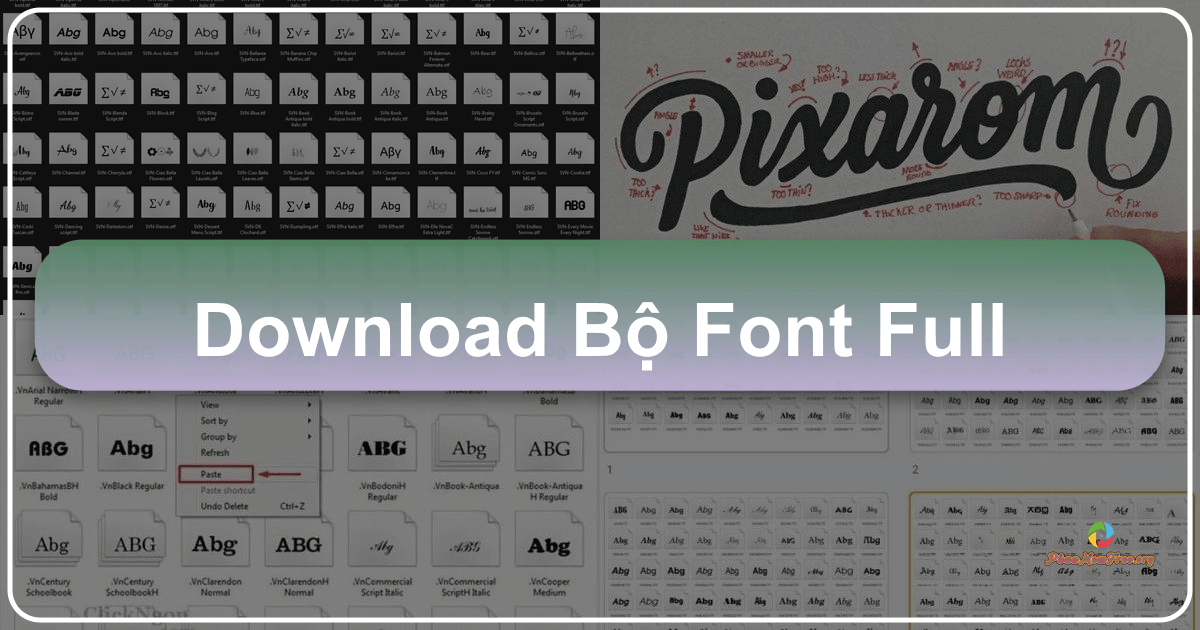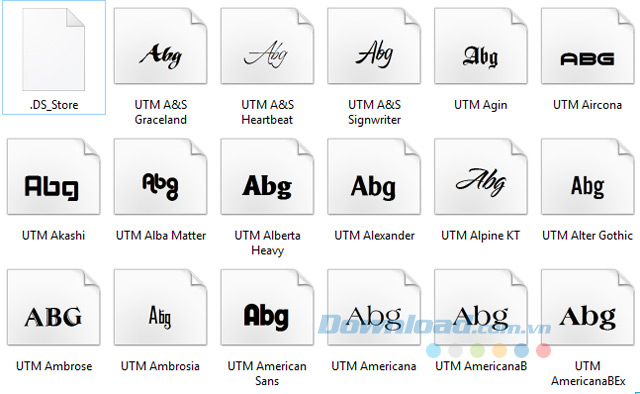
Bài viết này giới thiệu chi tiết về “Bộ Font Full”, một bộ sưu tập font chữ tiếng Việt phong phú và đa dạng, đáp ứng hầu hết nhu cầu sử dụng của người dùng. Bộ font này được cung cấp miễn phí, với dung lượng nhỏ gọn (5,2 MB) nhưng chứa đựng một kho tàng font chữ, giúp người dùng dễ dàng lựa chọn và sử dụng cho nhiều mục đích khác nhau. Tương thích với hầu hết các hệ điều hành Windows từ XP đến 11, Bộ Font Full là một công cụ hữu ích cho cả người dùng phổ thông lẫn các nhà thiết kế chuyên nghiệp.
Tổng quan về Bộ Font Full:
Bộ Font Full là một tập hợp khổng lồ các font chữ tiếng Việt phổ biến nhất hiện nay. Nó không chỉ bao gồm các font chữ cơ bản thường dùng trong soạn thảo văn bản, mà còn tích hợp nhiều font chữ nghệ thuật, font thư pháp, đáp ứng nhu cầu sáng tạo của các nhà thiết kế đồ họa, người làm thiết kế, hay đơn giản là những ai yêu thích sự đa dạng và độc đáo trong văn bản của mình.
Việc sở hữu Bộ Font Full giúp giải quyết triệt để vấn đề thiếu font chữ trên máy tính, một lỗi khá phổ biến gây ra nhiều khó khăn trong quá trình sử dụng máy tính. Thay vì phải tìm kiếm và tải từng font chữ riêng lẻ, gây mất thời gian và công sức, người dùng chỉ cần tải và cài đặt một lần duy nhất là có thể truy cập vào hàng trăm font chữ khác nhau, sẵn sàng phục vụ mọi nhu cầu.
Nội dung của Bộ Font Full:
Bộ Font Full bao gồm đầy đủ các loại font chữ thuộc nhiều bảng mã khác nhau, nổi bật là:
- Font Unicode: Đây là loại font chữ phổ biến nhất hiện nay, hỗ trợ hầu hết các ký tự tiếng Việt có dấu và các ngôn ngữ khác trên thế giới. Việc sử dụng font Unicode đảm bảo tính tương thích cao giữa các phần mềm và hệ điều hành khác nhau.
Font TCVN3: Đây là loại font chữ chuẩn của Việt Nam, được sử dụng rộng rãi trong các văn bản chính thức, tài liệu hành chính.
Font VNI: Một loại font chữ tiếng Việt phổ biến khác, được nhiều người sử dụng nhờ khả năng hiển thị tốt và độ tương thích cao.
Font UTM: Loại font chữ này cũng được tích hợp trong bộ Font Full, mang đến sự đa dạng về kiểu dáng và phong cách chữ viết. Đặc biệt, Bộ Font UTM nổi bật với nhiều kiểu chữ khác nhau, từ những kiểu chữ đơn giản đến những kiểu chữ nghệ thuật phức tạp.
Ngoài ra, Bộ Font Full còn chứa nhiều font chữ khác nhau về kiểu dáng, đáp ứng nhiều sở thích và mục đích sử dụng. Ví dụ, nếu bạn cần viết thư pháp, những kiểu chữ bay bổng, mềm mại, thì các font chữ thư pháp trong bộ Font Full sẽ là lựa chọn lý tưởng. Nếu bạn cần những font chữ đơn giản, dễ đọc cho văn bản thông thường, thì những font chữ như Time New Roman, Arial,… cũng có mặt đầy đủ.
Tính năng chính của Bộ Font Full:
- Hỗ trợ đa dạng font chữ tiếng Việt và tiếng Anh: Bộ Font Full không chỉ giới hạn ở các font chữ cơ bản mà còn bao gồm nhiều kiểu font chữ khác nhau, từ font chữ thông thường như Unicode, VNI, VnTime đến các font chữ nghệ thuật như font thư pháp, font nét bút, font ông đồ,… Sự đa dạng này giúp người dùng có nhiều lựa chọn phù hợp với từng mục đích sử dụng.
Kết luận:
Bộ Font Full là một bộ sưu tập font chữ tiếng Việt hoàn chỉnh và tiện dụng. Với sự đa dạng về kiểu dáng, độ tương thích cao và cách cài đặt đơn giản, Bộ Font Full là một công cụ hữu ích cho mọi người dùng, từ người dùng thông thường đến các nhà thiết kế chuyên nghiệp. Việc tải về và sử dụng Bộ Font Full sẽ giúp người dùng tiết kiệm thời gian, công sức và mang đến trải nghiệm soạn thảo văn bản tuyệt vời hơn.